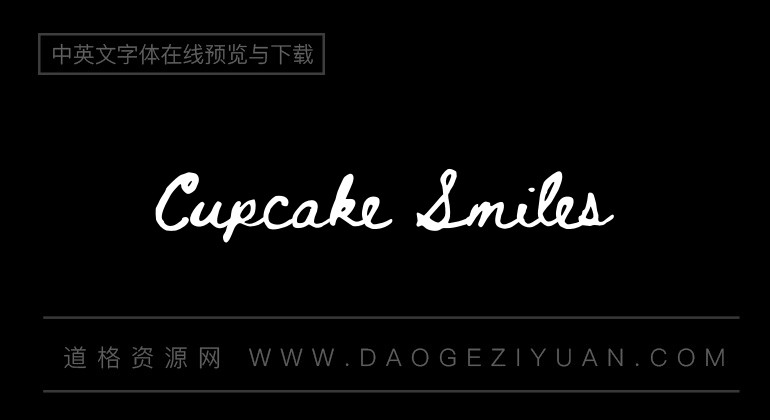
Cupcake Smiles是一种手写风格的英文字体,由Jonathan S. Harris于2015年设计。它的特点是圆润的线条和可爱的造型,适合用于卡片、海报、儿童书籍等需要表现出轻松、欢快、甜美氛围的场合。该字体有多种字重可供选择,包括Light、Regular、Bold、Black等,可以根据需要选择不同的字重来制作不同效果的设计作品。内容介绍
Cupcake Smiles是一款非常不错的手写艺术字体,具有很好的视觉感,适合于文化类的宣传设计、商业类品牌的广告和产品包装设计以及个性化文字排版等较多场景。